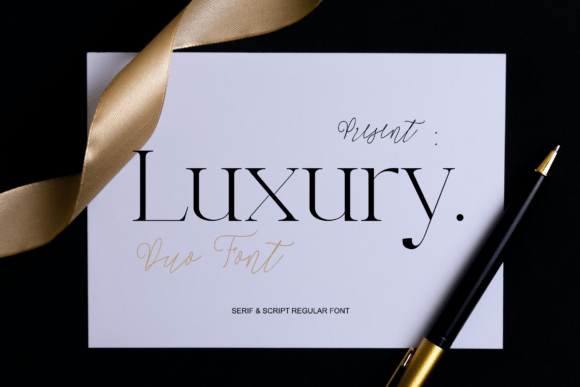
Luxury Duo
Présentation du Duo de Polices « Luxury » : Une Symphonie d’Élégance
Si vous cherchez une combinaison de polices qui incarne l’essence du raffinement, le duo « Luxury » est une sélection incontournable. Cette création unique marie l’élégance intemporelle d’une police série avec la fluidité gracieuse d’une écriture manuscrite, offrant une polyvalence exceptionnelle pour des projets haut de gamme. Que ce soit pour un branding sophistiqué, des invitations de mariage ou des designs éditoriaux, « Luxury » transforme chaque texte en une œuvre d’art visuelle.
La Police Série : Charme Intemporel et Structure Élaborée
- Caractère classique : La police série du duo « Luxury » allie des traits précis à des courbes harmonieuses, rappelant les typographies traditionnelles tout en conservant une modernité discrète.
- Idéale pour les titres : Sa lisibilité et son impact visuel en grand format en font une option parfaite pour les en-têtes, les logos ou les éléments graphiques majeurs.
- Adaptée aux designs intemporels : Qu’elle soit utilisée pour des cartes de visite, des emballages de luxe ou des affiches, elle évoque une distinction sans ostentation.
La Police Script : Éclat de Fluidité et Sensibilité
- Écriture manuscrite raffinée : Le script « Luxury » se distingue par ses traits fluides et ses terminaisons délicates, imitant la grâce d’une calligraphie maîtrisée.
- Parfum romantique : Idéale pour les projets personnalisés comme les invitations de mariage ou les cartes